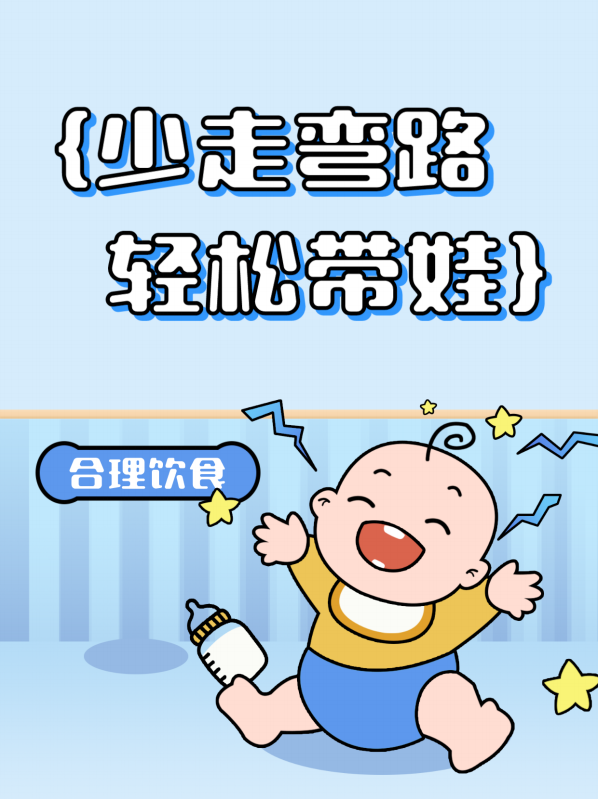
高手庆科墩墩体 大黑
Master-ZqkdundunGB Bold
字型略扁工整,布白均匀,中宫宽阔,重心平稳。整体简洁可爱,是一款圆体。字体在使用直线结构设计的同时对笔画进行了整体圆角的处理方式。横细竖粗,横竖笔画端点和笔画折笔处均运用圆角元素,使其笔画圆润饱满。字体内部留白均匀,适用范围广泛,具有良好的视觉效果,易于阅读。